런던의 타입페이스 디자인 듀오_A2/SW/HK
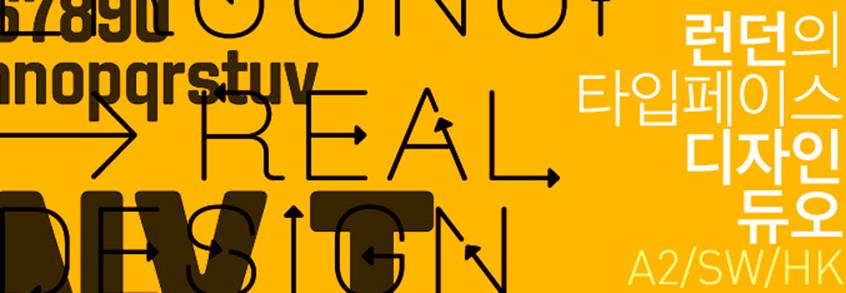
A2/SW/HK는 런던에 자리한 디자인 스튜디오이다. 로얄 예술대학(Royal College of Art)에서 만난 스캇 윌리엄스(Scott Williams)와 헨릭 쿠벨(Henrik Kubel), 이 듀오 디자이너가 운영하는 A2/SW/HK는 브랜딩, 출판, 전시, 웹디자인, 각종 미디어매체 등에 사용되는 디자인과 타입페이스를 제작하는 회사이다. 뉴욕현대미술관, 펭귄프레스, 보그, 런던디자인뮤지엄 등 전세계 선도적인 클라이언트와 협업하며 감각적인 타입페이스를 선보이고 있는 그들은 현재 글로벌 업계가 주목하고 있는 젊은 디자인 스튜디오 중 하나이다.
1. 두 사람은 어떻게 만났고, 함께 일을 시작하게 된 계기는 무엇인가요?
우리는 1998년 로얄예술대학(Royal College of Art) 커뮤니케이션 아트 & 디자인 학부에서 만났습니다. 이미 대학에서부터 여러 행사, 전시 포스터 작업을 함께 했었고, 졸업과 함께 2000년 바로 디자인 스튜디오 A2/SW/HK를 설립해 지금까지 오게 되었습니다.
2. A2/SW/HK는 맞춤 제작 형 타입페이스로 많은 클라이언트와 함께 하는 것으로 알고 있는데, 대표적으로 어떤 작품들이 있나요?
말씀하신 대로 저희 작업의 대부분은 클라이언트의 맞춤 의뢰로 이뤄집니다. 그 대상으로는 책, 카탈로그, 신문, 매거진, 전시, 사인시스템, 브랜딩, 우표 등 다양합니다. 뉴욕현대미술관(MoMA), 대니시포스트(Danish Post), 런던디자인뮤지엄(Design Museum, London), 월페이퍼매거진(Wallpaper*), 펭귄프레스(Penguin Press), 테이트모던(Tate Modern), V&A 뮤지엄(V&A Museum) 등 전세계 유수의 클라이언트들이 저희와 함께 작업을 해왔습니다. 대표적으로 몇 가지 선보이자면, 펭귄프레스에서 출간된 자디 스미스(Zadie Smith)의 책 ‘On Beauty’에 쓰인 A2 Zadie, 런던의 아트매거진 ‘afterall’ 시리즈, 아일랜드 작가 사무엘 베켓(Samuel Beckett)의 전집에 사용된 A2 Beckett, 런던디자인뮤지엄에서 열린 전시 ‘Ergonomics – Real Design’ 때 쓰인 A2 Ergonomics 등이 있습니다. 이외에도 많은 작업들이 있죠.
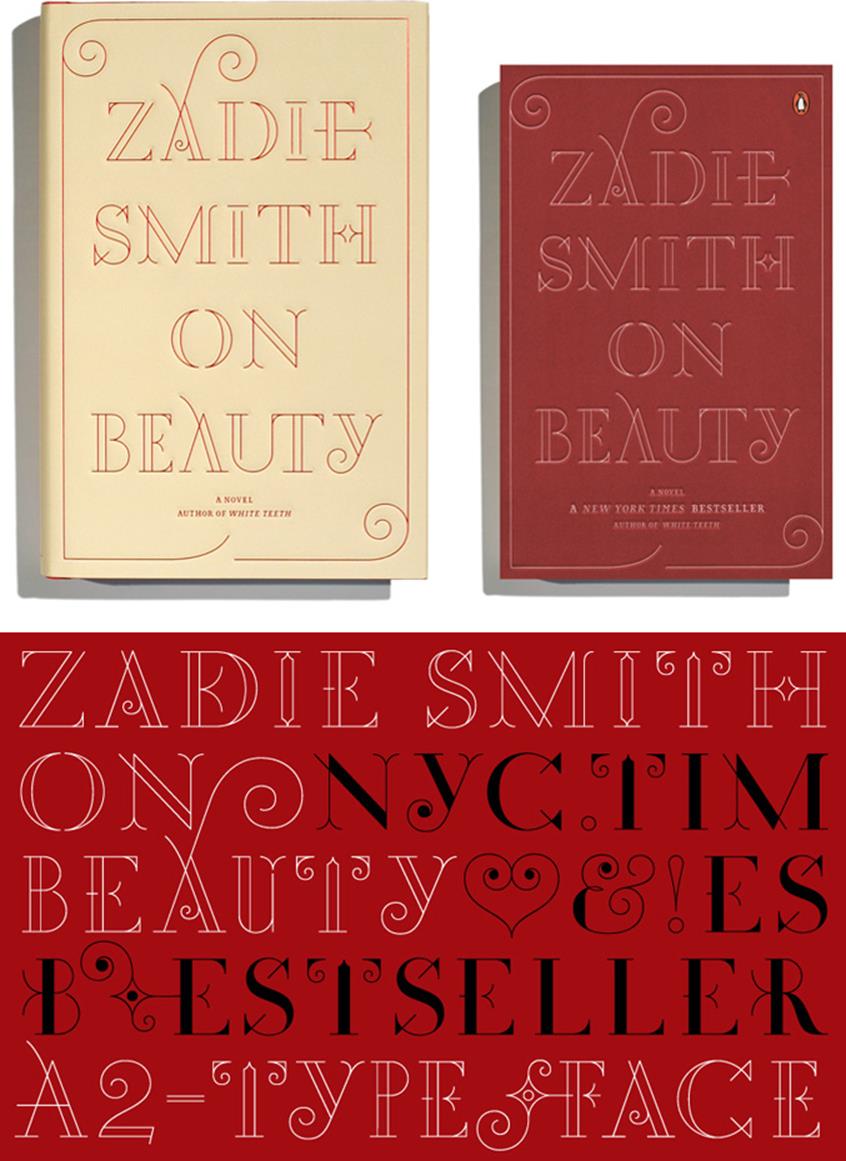
Typeface name: A2 Zadie
Client: Penguin Press, NYC
Project: Zadie Smith ‘On Beauty’ novel
Year: 2005
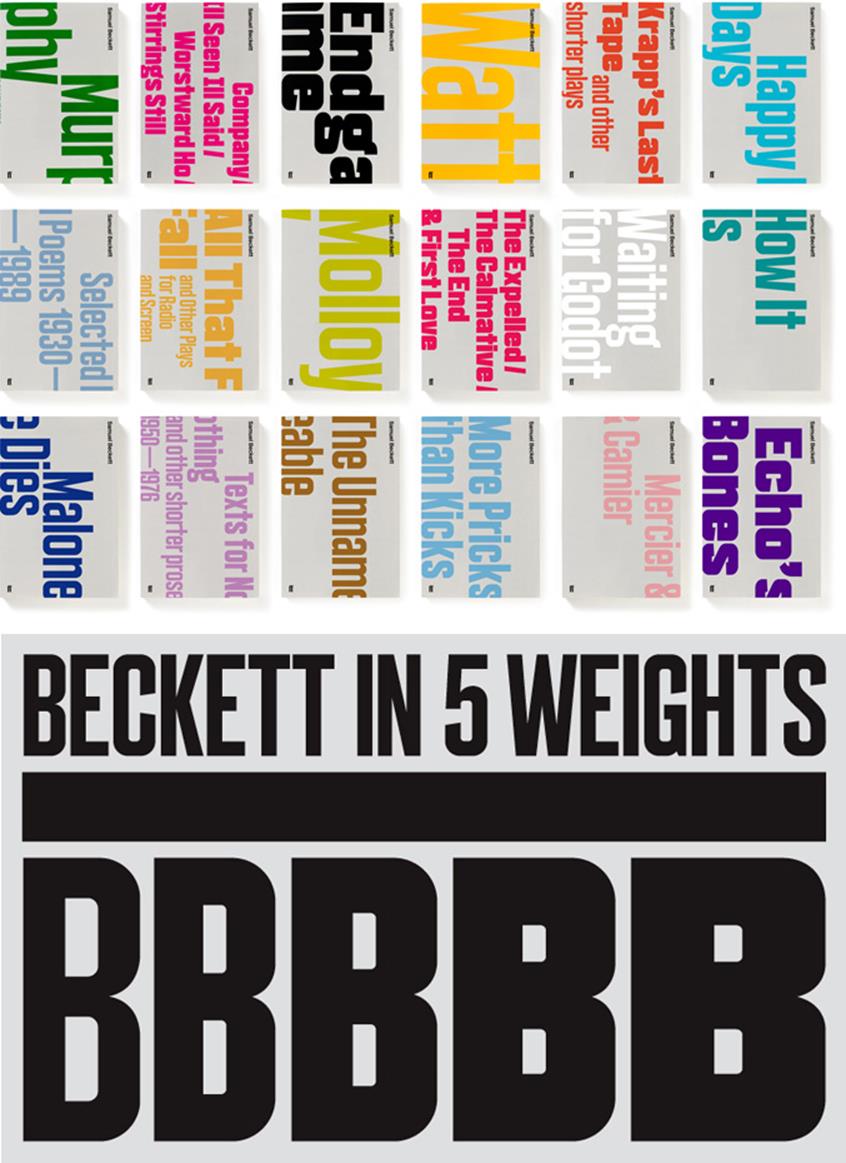
Typeface name: A2 Beckett
Client: Faber & Faber
Project: Typeface for Samuel Beckett complete works, 18 book covers
Year: 2009
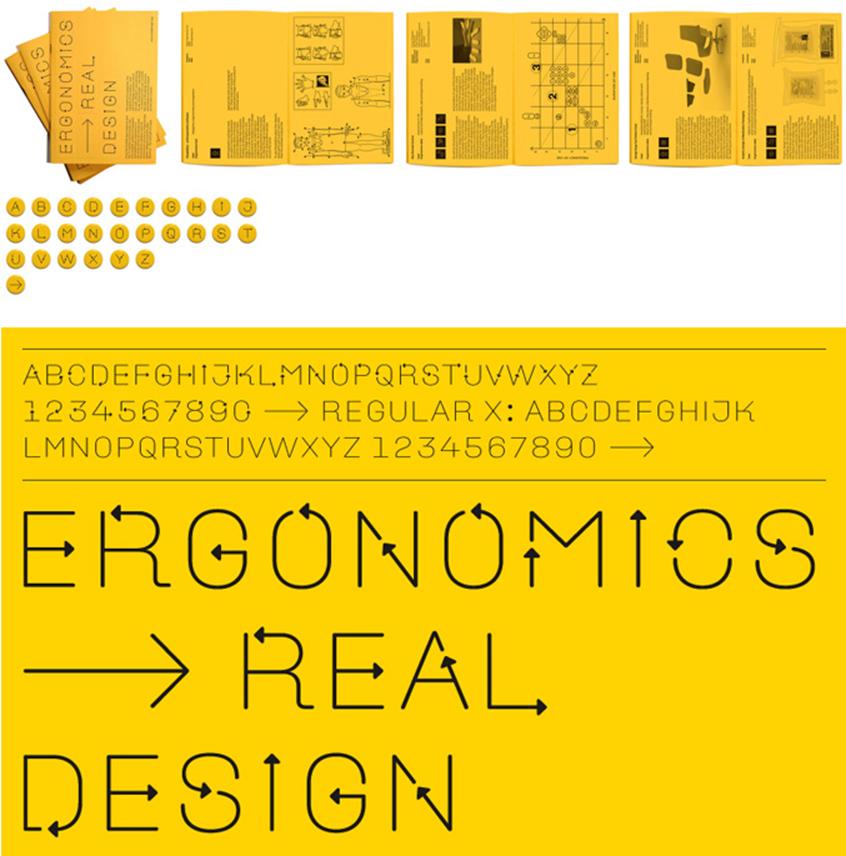
Typeface name: A2 Ergonomics
Client: Design Museum, London
Project: Exhibition identity and applied graphics for ‘Ergonomics | Real Design’ exhibition
Year: 2009
3. 몇 해전 ‘New Rail Alphabet’을 통해 업계의 많은 주목을 받았는데, 어떤 프로젝트였나요?
뉴 레일 알파벳(New Rail Alphabet)은 1960년대 초 마가렛 칼버트(Margaret Calvert)가 디자인했던 브리티쉬 레일 알파벳(British Rail alphabet)의 리바이벌 버전입니다. 레일 알파벳은 원래는 런던 사인체계의 필수적인 요소로 만들어진 타입페이스로, 영국국립병원에서 처음 사용되었죠. 그러다가 BAA공항부터 영국 국영 철도와 덴마크의 철도역에 까지 쓰이게 된 것입니다.
저희가 이 타입페이스를 리바이벌하기 위해 칼버트와 접촉한 게 2005년이었습니다. 전시와 카탈로그에 사용하기 위한 목적이었죠. 그러나 한동안 작업은 진행되지 않았습니다. 다른 스페인 업체도 레일 알파벳을 리바이벌하기 위해 칼버트와 접촉 중이었던 것입니다. 결국 우여곡절 끝에 2008년에 이르러서야 작업을 다시 시작할 수 있었습니다. 칼버트와의 긴밀한 협업 속에 태어난 뉴 레일 알파벳은 오프 화이트(Off White), 화이트(White), 라이트(Light), 미디움(Medium), 볼드(Bold), 블랙(Black)의 6개 두께로 숫자와 이탤릭을 포함한 구성으로 이루어집니다. 특히 라이트, 미디움, 볼드는 칼버트가 1980년에 제작한 슬라브 세리프체인 모노타입 칼버트(Monotype Calvert)와 매치를 이루기도 합니다. 뉴 레일 알파벳은 이제 저희 A2/SW/HK의 트레이드 마크가 되었습니다.
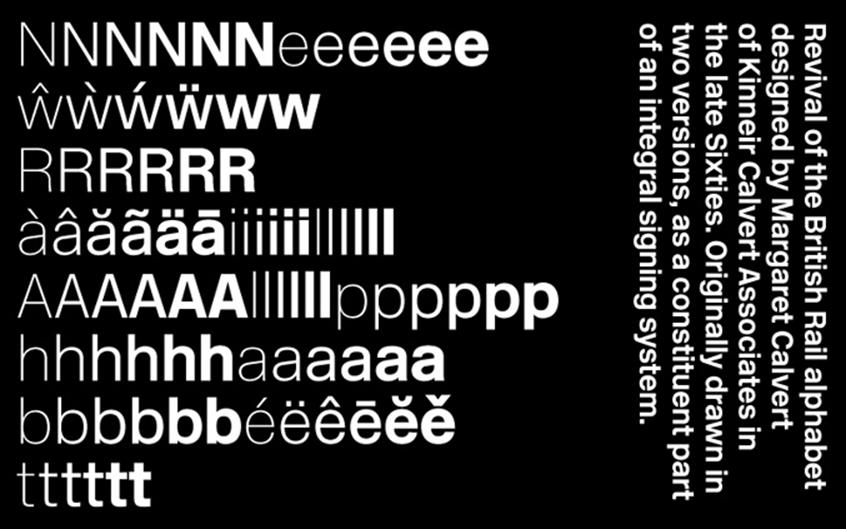
Typeface name: New Rail Alphabet
Designed in collaboration with Margaret Calvert
Client: A2-TYPE
Project: Revival of Rail Alphabet designed in the early Sixties by Margaret Calvert of Kinneir Calvert Associates.
Year: 2009
4. 지난해 가을 A2-Type을 세웠습니다. 디자인 사학자 폴 쇼가 2010년 10대 타이포그래피 사건으로 꼽았을 정도로 큰 이슈였는데, 설립 목적은 무엇인가요?
A2/SW/HK는 디자인 작업을 합니다. 그 안에 타입페이스 제작이 들어있는 것입니다. A2-Type은 디자인 작업을 하면서 만든 타입페이스를 출시하고 판매하는 플랫폼의 자회사라고 보시면 됩니다. 여러 해 동안 많은 타입페이스를 제작했고, 그것을 따로 선보이기 위한 목적으로 A2-Type의 설립은 자연스러운 흐름이었죠. 아직 긴 시간이 지난 것은 아니지만 A2-Type을 통해 전세계 많은 디자이너들이 저희 타입페이스들을 구매하여 사용하고 있습니다. 또한 덕분에 더 많은 클라이언트들의 의뢰가 들어오고 있습니다. 저희로선 아주 흥분되는 발전인 셈이죠. 올해 5월에는 웹 폰트를 판매하기 위해 웹 잉크(WebINK)와 파트너쉽을 체결하기도 했습니다. http://www.extensis.com/en/WebINK/fonts/foundry.jsp?foundry=A2-Type
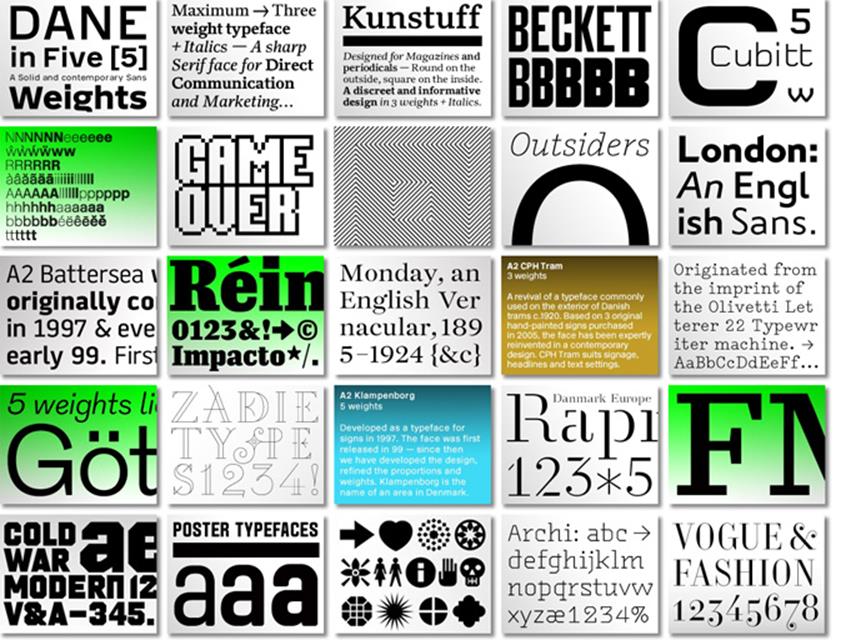
5. 많은 작업들 중 개인적으로 가장 만족하는 프로젝트가 있다면?
쿠벨 : 특별히 어느 것이 최고였다고 말하기가 애매합니다.
윌리엄스 : 개인적으로 가장 도전적이고 가치 있었다고 생각되는 것은 ‘Turner Prize Exhibition’에서 인쇄 캠페인을 벌였던 ‘Reading Room’ 프로젝트입니다.
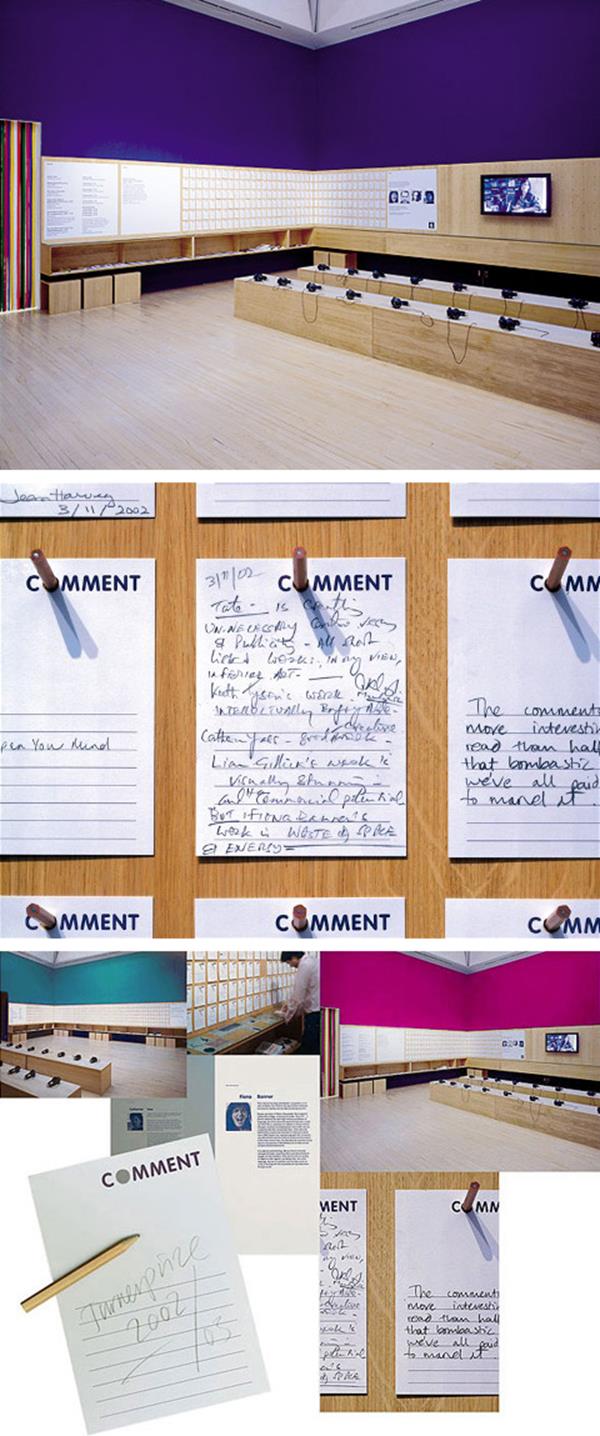
Turner Prize Exhibition design, 2002—07
Tate Britain, London
Spatial design, applied graphics and print campaign
6. 많은 사람들이 서체 시장이 곧 포화상태로 접어들 것이라 생각합니다. 이에 대한 의견을 묻고 싶습니다.
쿠벨 : 타입페이스 디자인은 우리가 살고 있는 세상을 반영합니다. 그것은 또한 한나라의 문화와 정체성의 거울이기도 합니다. 패션, 예술, 음악과 기술이 언제나 진화하듯, 타입페이스 디자인 역시 그럴 것입니다. 언제나 새로운 방향과 창의적인 생각을 위한 여지는 남아있기 마련이죠.
윌리엄스 : 돌아보면 산업혁명 때도 사람들은 그렇게 얘기했습니다. 그러나 그렇지 않았죠.
7. 현재 진행 중인 작업은? 혹은 앞으로의 계획은?
15세기의 훌륭한 타입페이스들을 현대적인 비율로 다시 만드는 작업을 하고 있습니다. 패밀리로 구성될 이번 작업은 북, 매거진, 아트 카탈로그 등에 쓰여질 것입니다.
8. 선호하는 디자이너나 타입페이스가 있나요?
쿠벨 : 캐슬론(Caslon), 길(Gill), 그리포(Griffo), 얀슨(Janson), 키스(Kis), 카터(Carter), 벤톤(Benton), 칼버트(Calvert)… 언급하기에 너무 많습니다.
윌리엄스 : 개인적인 선호는 없습니다. 단지 모두 존경할 뿐이죠.
9. 작업 프로세스에 대해 설명 부탁드립니다.
쿠벨 : Idiom(목적의 정의), Process(스케치, 아이디어, 드로잉), Result(테스트, 응용, 출시)
윌리엄스 : 프로젝트에 따라 그에 맞게 달라집니다.
10. 개인적인 디자인 철학이 있다면?
쿠벨 : 심플함을 추구하라.
윌리엄스 : 꾸준히 작업하라.
11. 마지막으로 타입페이스 디자인을 시작하는 디자이너 혹은 학생들에게 조언을 해주신다면?
쿠벨 : 대가도 좋고, 신인도 좋습니다. 다른 타입디자이너들의 작업을 연구하세요. 저는 개인적으로 시대를 막론하고 타입페이스 디자인의 다양하고 많은 스타일을 섭렵하려고 노력했습니다. 타입페이스 디자인의 각각의 시대와 스타일은 서로 다른 가르침을 줄 수 있기 때문입니다.
윌리엄스 : 타입페이스 디자인 역사를 두려워하지 마세요. 그것을 끌어들이고, 자세히 살펴보세요. 그리고 자기만의 목소리로 발전시키세요.
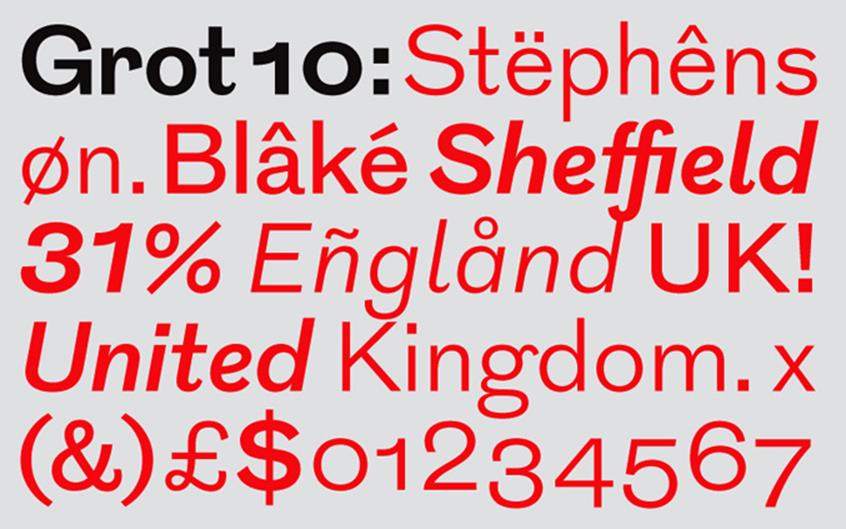
Typeface name: A2 Grot10
Client: A2-TYPE
Project: Text typeface for commercial release
Year: 2010
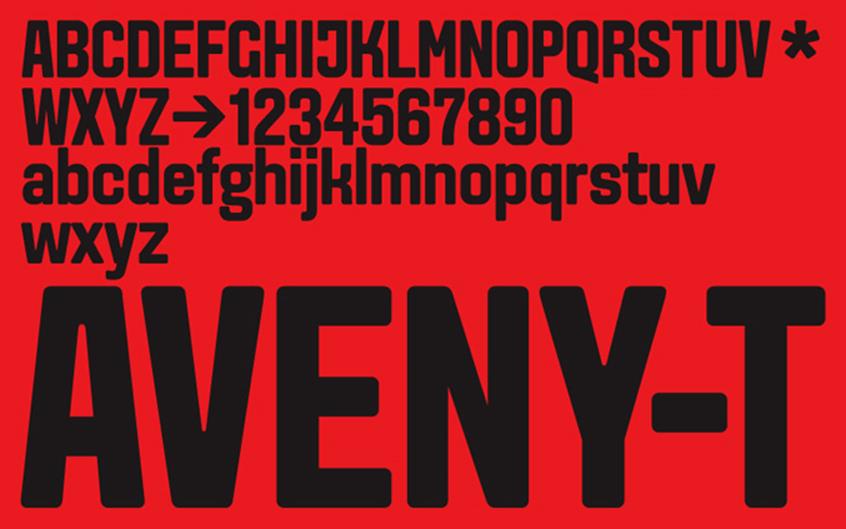
Typeface name: A2 Aveny-T
Client: Aveny-T Theatre
Project: Typeface for contemporary theatre in Copenhagen
Year: 2000
Typeface name: A2 London
Client: Vogue UK
Project: Sketch for a new display typeface
Year: 2006
Typeface name: A2 Flowers
Client:Various, Nørrebro Bryghus
Project: Printers flowers and illustrations for various clients and publications
Year: 2005
Typeface name: A2 Danmark
Client:Danish Post
Project: A set of 4 stamps for Louisiana Museum of Modern Art in Denmark
Year: 2008
Typeface name: A2 CPH Tram
Client:Kissmeyer Beer & Brewing
Project: Identity and packaging design
Year: 2009/11